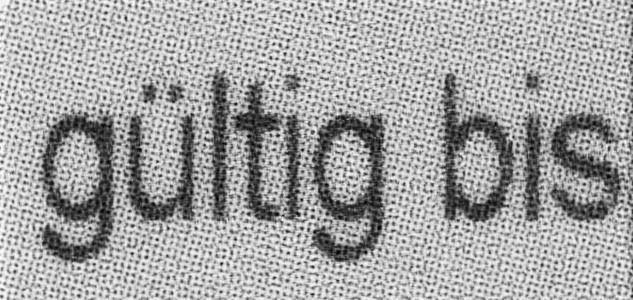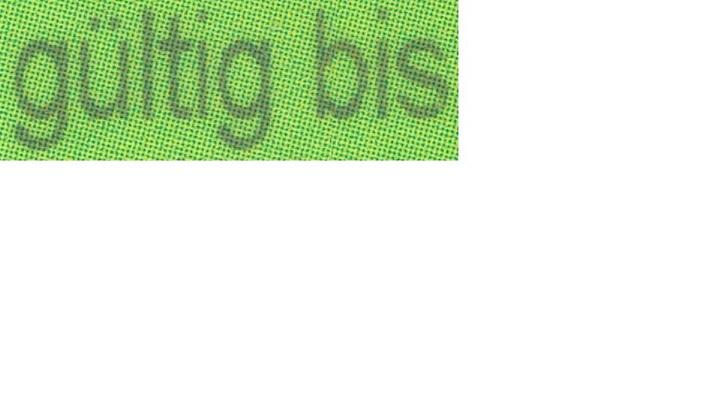
schrifart gesucht (gültig bis)
hallo suche folgende schriftart, erkennungsprogramme und seiten haben mir bislang nicht weiterhelfen können...
Hast du einen größeren Ausschnitt oder eine Quelle?
quelle leider nicht... konnte es nur verbessern das bild hoffentlich hilfts
Könnte das die Arial Narrow sein?
Ach? Wozu brauchst du dann die Schrift? :-?
Die Arials scheiden aus, weil dort ü- und i-Punkte und l, t, b oben bündig sind. Das ist beim gezeigten Muster nicht so.
Die Hintergrundfarbe berücksichtigend, würde ich aber auf einen Gutschein oder eine Eintrittskarte tippen. Vielleicht eine Kinokarte für keine bestimmte Vorstellung. Irgend etwas, auf dem nicht nur wenig Platz für einen größeren Schriftgrad, sondern auch wenig Platz für eine Schrift mit größerer Laufweite ist. Jedenfalls deutet das Raster auf einen sehr kleinen Schriftgrad hin.
Und wenn man die Verhältnisse von Querstrich zu Balken beim t und in den Rundungen sieht, scheint es keine Narrow zu sein sondern auf jeden Fall gequetscht.
Du musst doch wissen woher du du das Beispiel hast … ?